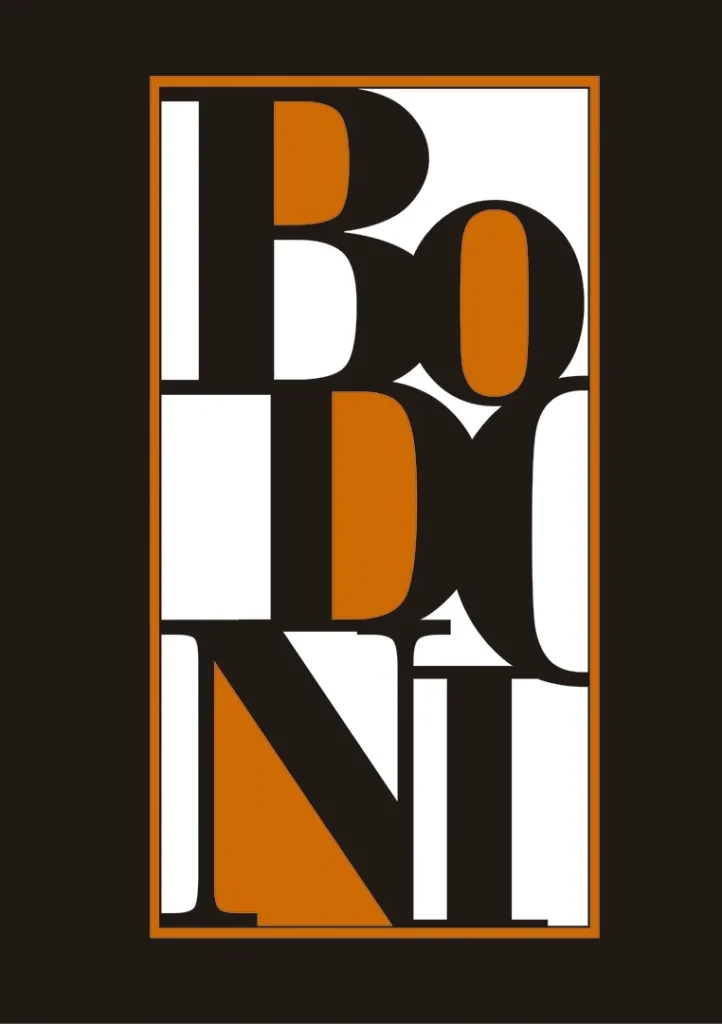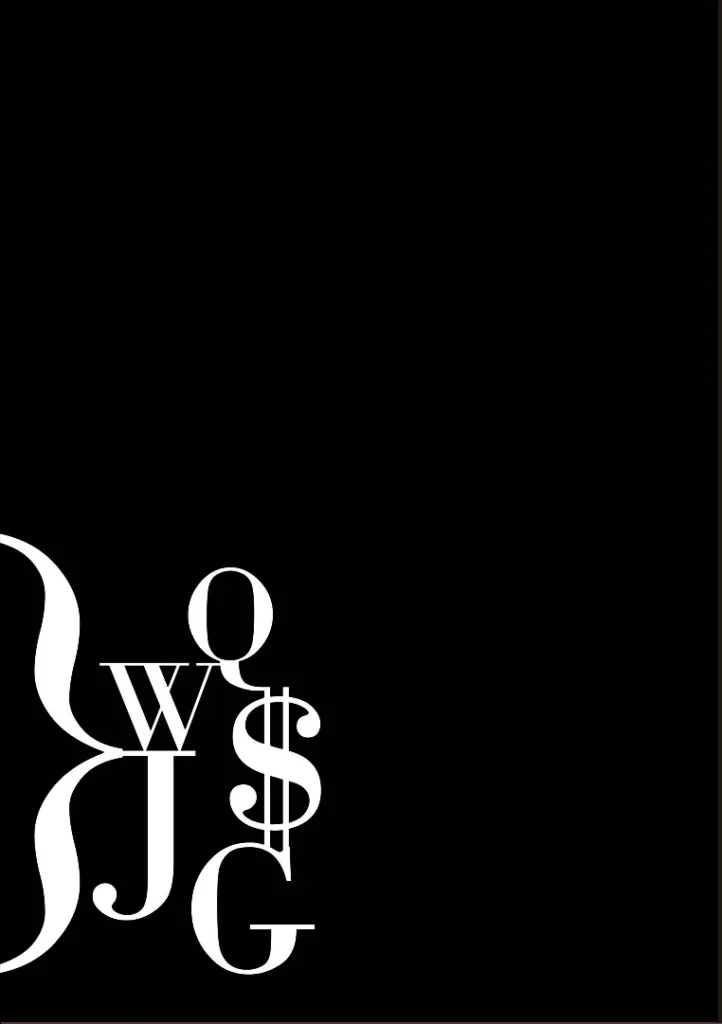
Su diseñador, Giambattista Bodoni (1740-1813) comenzó una trayectoria como director de la Stamperia Reale de Parma. Su obra, basada en los antecedentes de Fournier y de Baskerville, dará forma al espíritu formal de su época: delicado y elegante a la vez que con dramáticos contrastes.
Entre las versiones existentes hoy en día, la más lograda quizás sea la Bauer Bodoni, diseñada en 1926 por Heinrich Jost para la Fundición Bauer. Otros tipógrafos como Morris Fuller Benton (1914-16, para la American Type Founders) o Berthold Staff (1930) también hicieron versiones de la Bodoni.